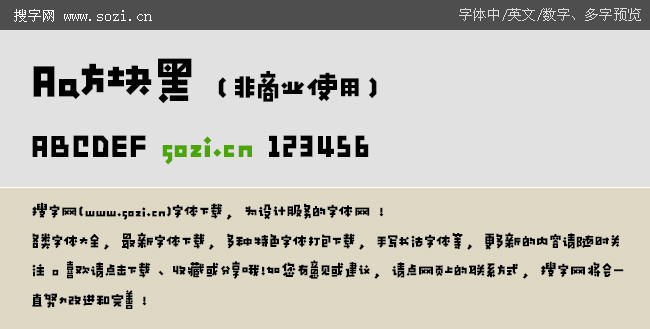
Aa方塊黑
搜字網(wǎng)給大家提供一款A(yù)a方塊黑(非商業(yè)使用)中文字體下載,該字體是一款卡通中文字體,字型大小錯(cuò)落有致、筆畫(huà)非常有趣,極具個(gè)性,適合兒童書(shū)裝設(shè)計(jì)、兒童包裝、海報(bào)設(shè)計(jì)等應(yīng)用(此字體為個(gè)人非商用版,商用可以聯(lián)系QQ:1006760504)。